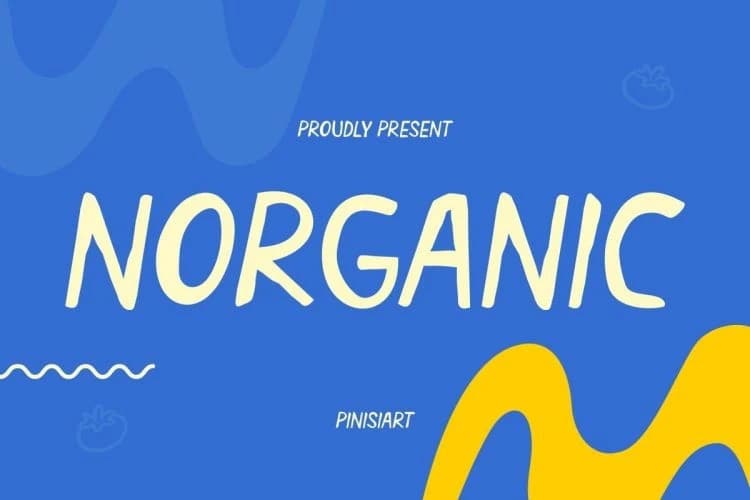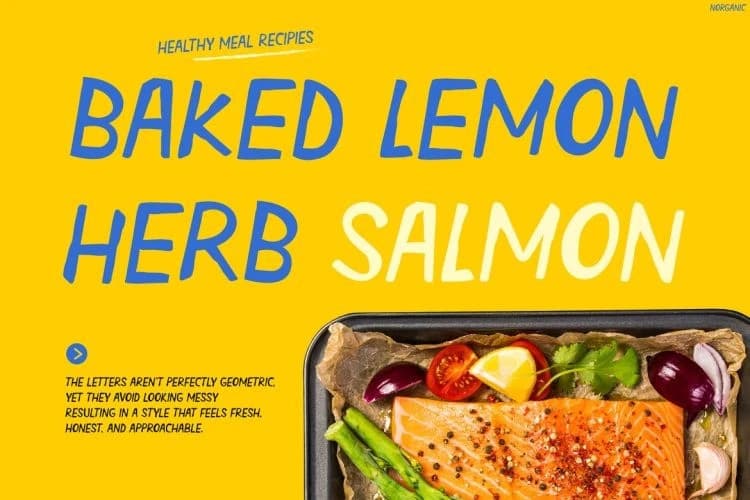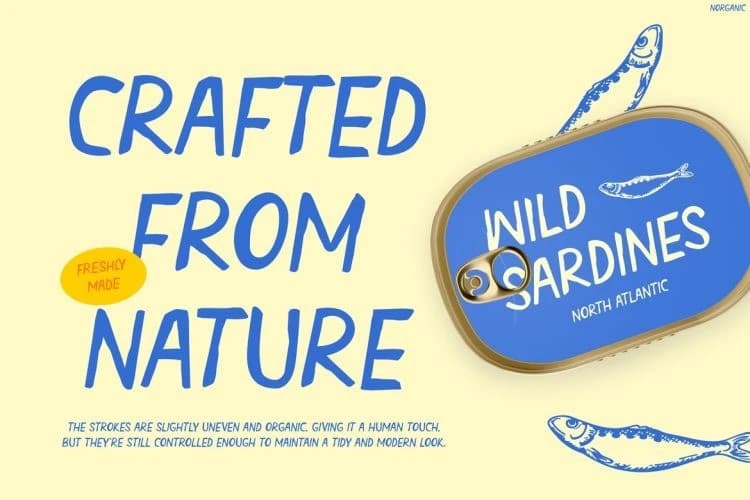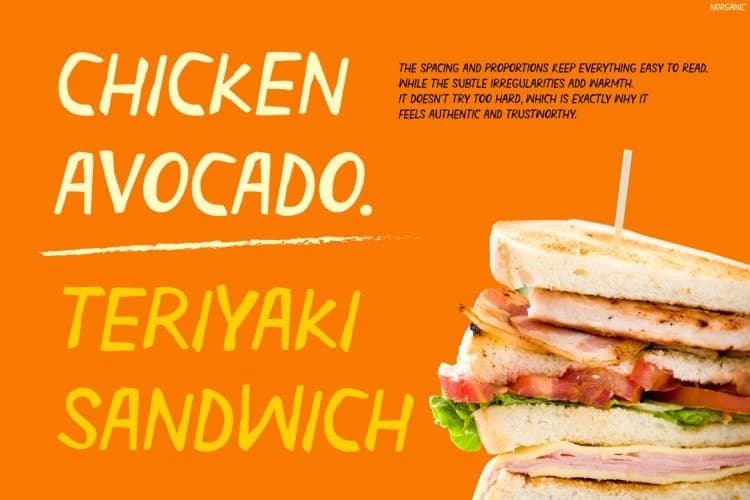
Norganic Kids Font
Norganic Kids Font, el ile çizilmiş çizgiler ve doğal kusurlu hatlar ile taze ve canlı bir his getirir. Temiz ama sıradışı şekilleri onu çekici ve okunması kolay kılar. Bu nedenle yazı tipi modern, dostane ve eğlenceli bir hava verir.
Norganic Kids Font, el çizimi çizgiler ve doğal kusurlu hatlarla taze ve canlı bir his sunar. Temiz ama tuhaf şekilleri onu ilgi çekici ve kolay okunabilir kılar. Bu nedenle font modern, dost canlısı ve eğlenceli bir his verir.